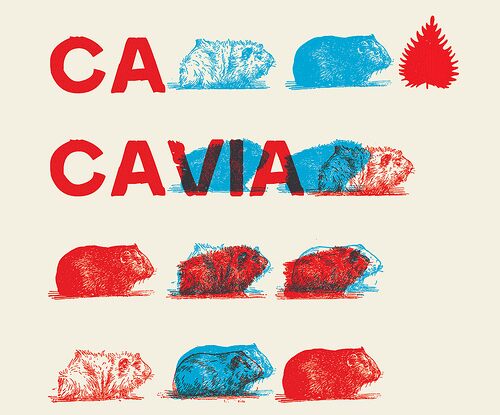
Cacavia 01 di Typeface è un font display gratuito e dall'aspetto eroso, caratterizzato da grandi capitali in blocco con bordi scheggiati e lati graffiati che fanno sembrare le lettere consumate dall'uso, piuttosto che invecchiate artificialmente. Le forme rimangono asciutte ed essenziali, lasciando che la texture ruvida parli da sola e doni al font un carattere secco, ideale per poster e locandine.
È perfetto per flyer musicali, grafiche skate e streetwear, copertine di zine, poster di eventi e titoli dove un font con questo grado di abrasione riesce a definire l'atmosfera da solo. Poiché le lettere sono larghe ed essenziali, funziona bene anche per titoli brevi e monogrammi che richiedono grinta senza risultare troppo eccentrici.